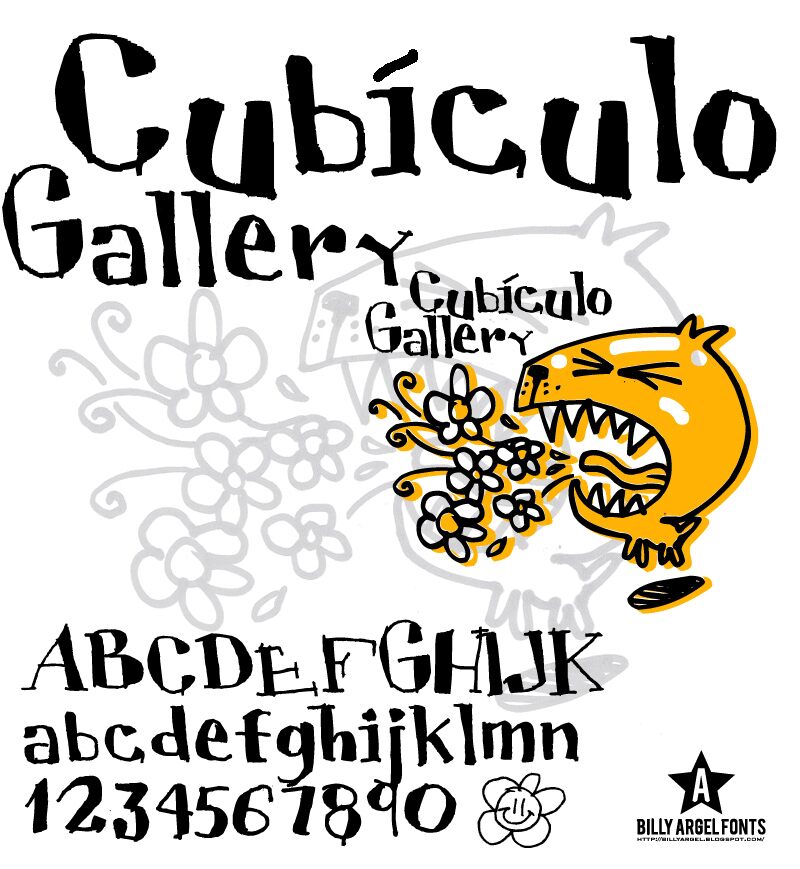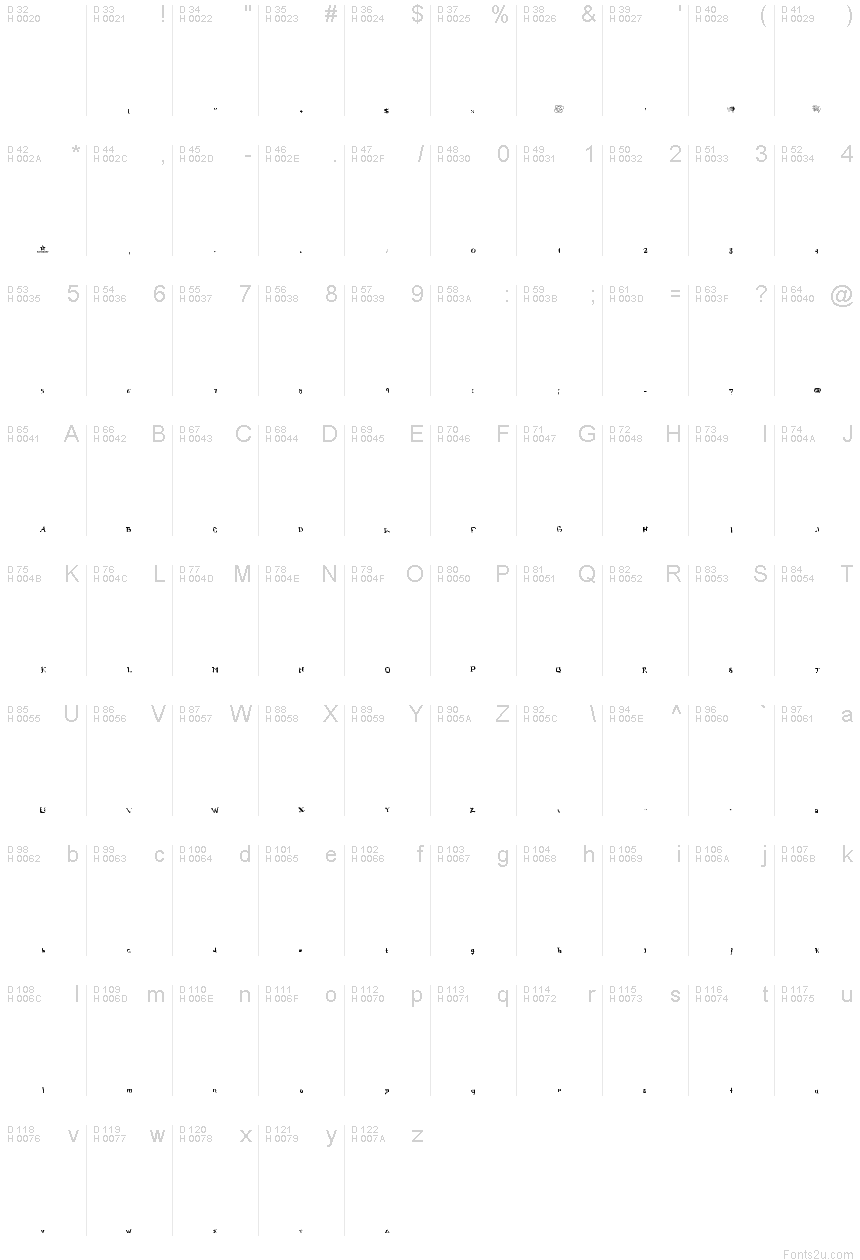
CUBICULOGALLERY SERIF
Cubiculo Gallery Serif autorstwa Billy Argel to darmowy, zniekształcony krój szeryfowy typu display z nutą klimatu starych plakatów. Wielkie litery sprawiają wrażenie ściśniętych, powykrzywianych i nieco nieposkromionych, a klinowate szeryfy i nierówne krzywizny nadają im wygląd jakby były wyryte, odbite z matrycy, a nawet lekko upiorne.
Dzięki temu czcionka naturalnie wpisuje się w horrory na ulotkach, nietuzinkowe okładki książek, opakowania na Halloween, plakaty muzyczne i plansze tytułowe, gdzie zwykły darmowy font wydawałby się zbyt grzeczny. Sprawdza się również w krótkich nagłówkach i monogramach, ponieważ litery niosą w sobie wystarczająco dużo dziwnego napięcia i smaku dawnego druku, by wykonać zadanie przy zaledwie kilku znakach.